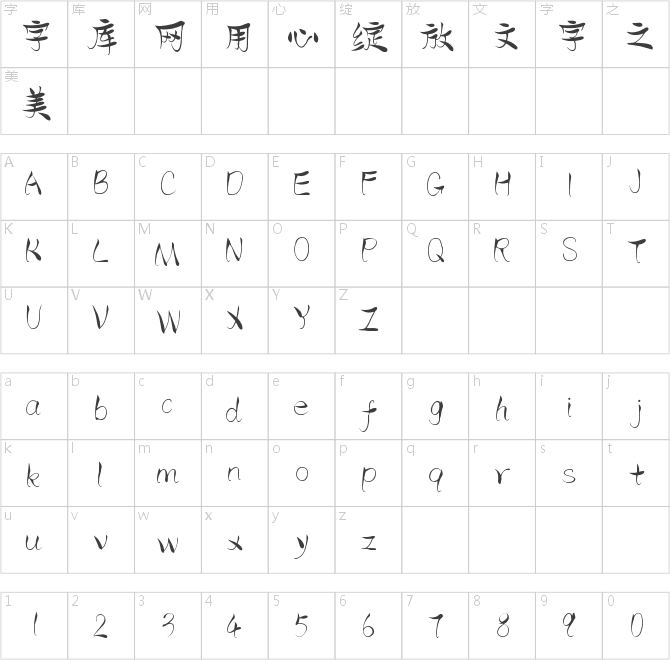
字魂257号-妙语手书
• 字魂257号-妙语手书是一款手写字,字形瘦长,笔画简洁有力,风格鲜明,造型巧妙有创新力,有着较好的应用空间,适用于品牌广告和产品包装设计,以及社交网络的个性化用字。
字魂257号-妙语手书字体ZiHun257Hao-MiaoYuShouShu字库是一款让人赏心悦目、百看不厌的中文字体,适合各类广告和产品包装设计应用,字体大小17.6MB,格式为ttf字体,上传用户是Elieen,作者/版权方为字魂